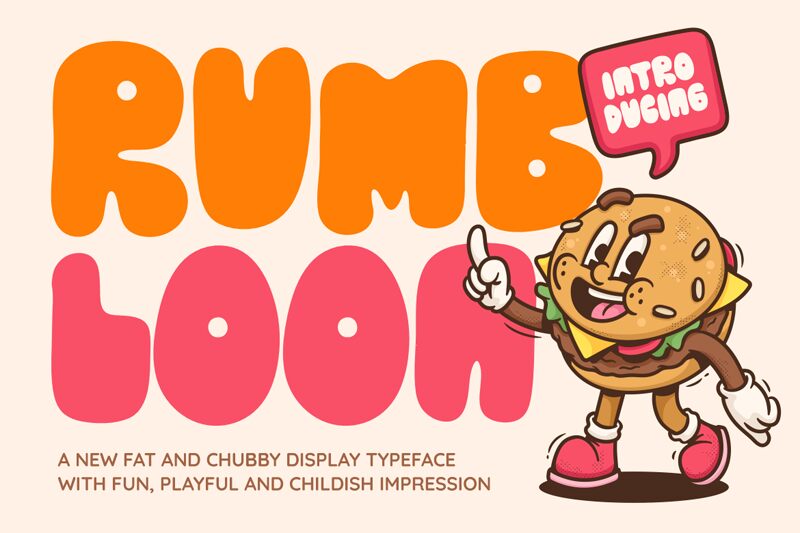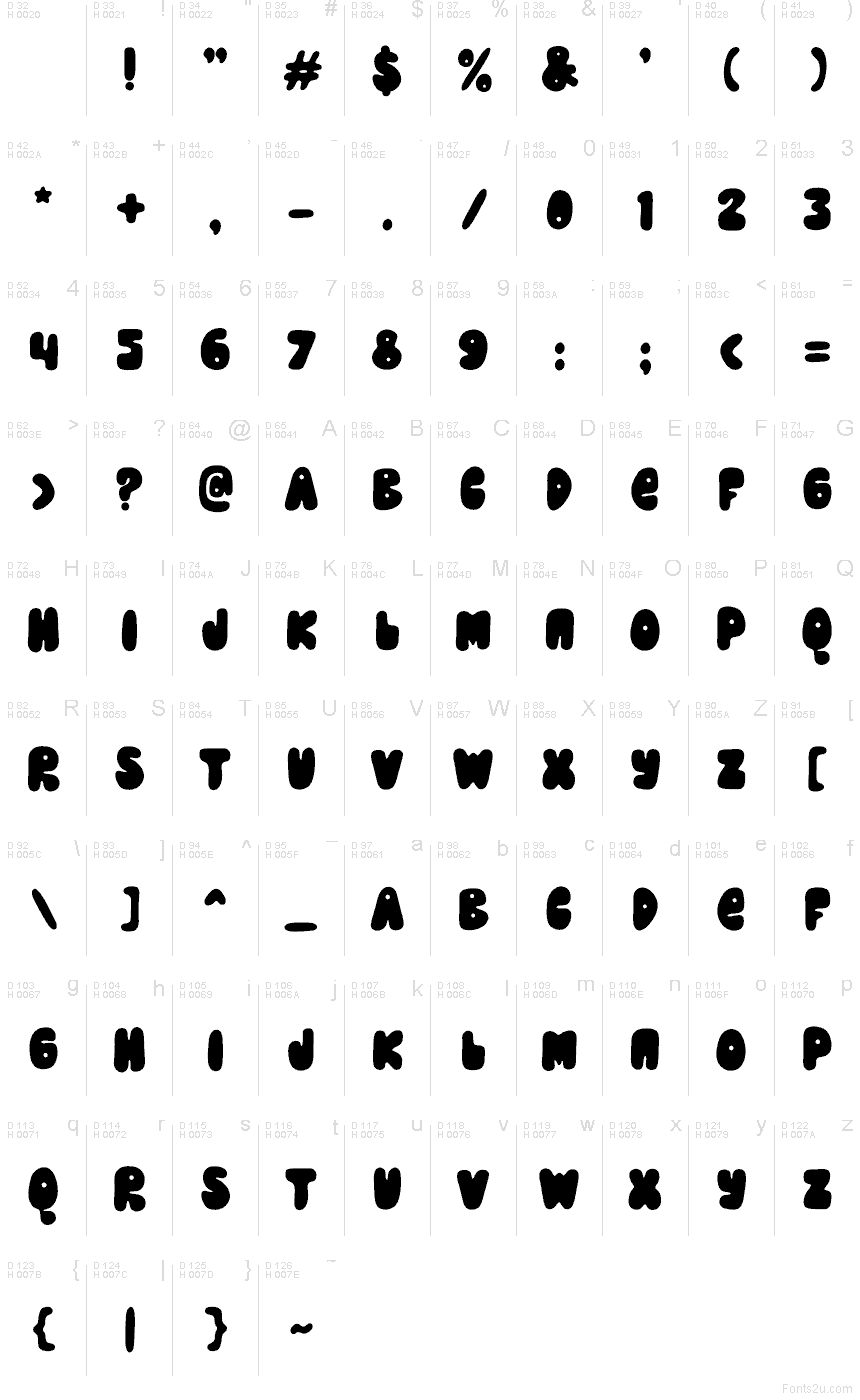
Rumbloon
Rumbloon от Shanaf Studio — это бесплатный мультяшный дисплейный шрифт с крупными «дутыми» заглавными буквами и дружелюбным настроением в стиле ретро-комиксов. Буквы выглядят мягкими и объемными, с глубокими закругленными изгибами, солидной толщиной и слегка прыгающим ритмом, который делает надпись игривой, а не слишком строгой.
Он отлично подходит для заголовков плакатов, детского брендинга, упаковки снеков, приглашений на вечеринки и обложек для YouTube, где нужен бесплатный шрифт, создающий настроение «на лету» без лишнего декора. Дутые заглавные также хороши для заголовков и коротких логотипов, так как их плотный силуэт и игрушечный характер доносят суть даже в коротких словах.